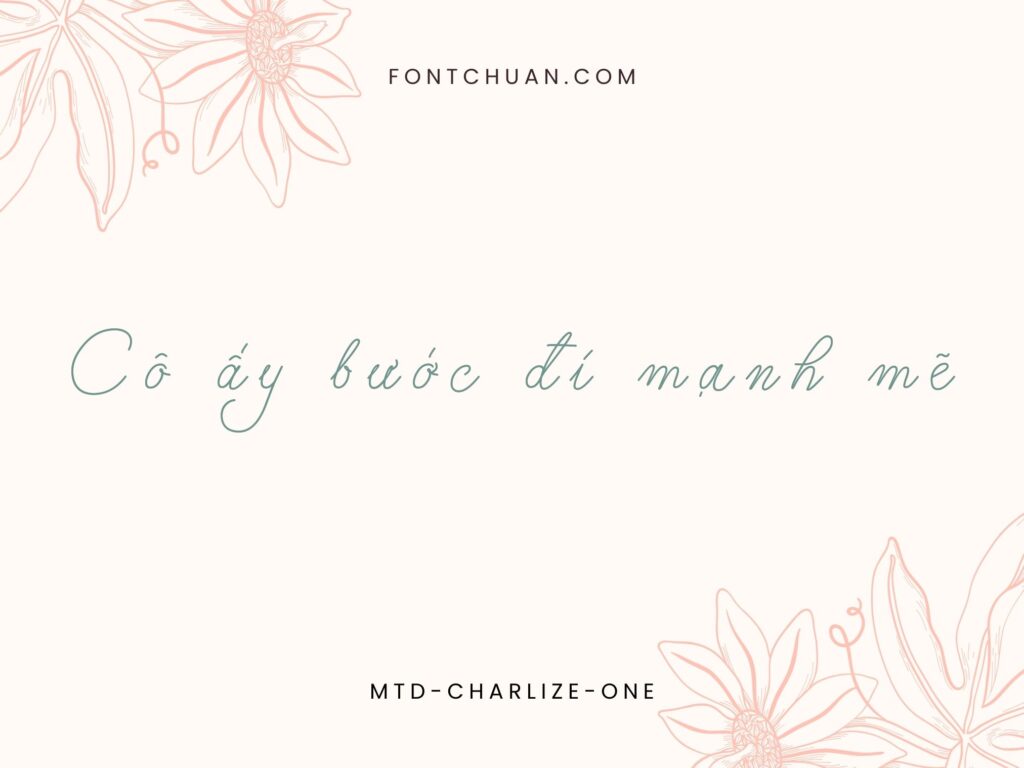
Font MTD Charlize One Việt Hóa
Font MTD Charlize One là một kiểu chữ viết tay thanh lịch, được thiết kế với phong cách calligraphy tinh tế. Font này hỗ trợ đầy đủ tiếng Việt cùng hơn 90 ngôn ngữ khác, mở rộng khả năng ứng dụng trong các thiết kế đa ngôn ngữ. Đây là một trong những phông chữ được cộng đồng thiết kế đánh giá cao và sử dụng trong nhiều dự án sáng tạo, đáp ứng nhu cầu đa dạng của người dùng.
MTD Charlize One nổi bật với các đường nét mềm mại và uyển chuyển, tạo cảm giác sang trọng và nghệ thuật. Font rất phù hợp cho các thiết kế logo, tiêu đề, bao bì sản phẩm, thiệp mời và các ấn phẩm đòi hỏi sự tinh tế và độc đáo. Các ngành nghề phù hợp bao gồm quảng cáo, giáo dục, công nghệ, thiệp cưới và ảnh cưới. Font này cũng lý tưởng cho các sự kiện như Tết, Giáng sinh, Valentine và các lễ hội khác.